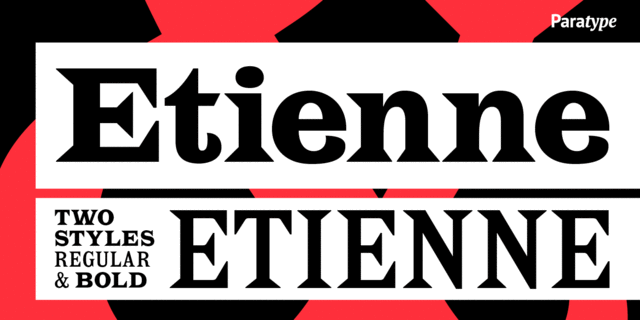
Шрифт разработан по мотивам рисунков гарнитуры Антик №8 и других подобных шрифтов XIX века (Латин Антик, Широкий Латин, Узкий Этьен, Широкий Ренессанс) для фирмы ParaType в 2002 году (дизайнер Тагир Сафаев). Шрифт так называемого латинского типа, с мощными треугольными засечками и довольно необычными завитками у некоторых строчных знаков. Тем не менее он великолепно подходит для широкого ассортимента работ в акцидении и рекламе.
Ассоциации c семейством EtienneКачества и характер:
острый, интересный, характерный, манерный, вычурный, причудливый, чудной, звонкий, оригинальный, старомодный, старинный, исторический, заметный, броский, азартный, резкий
Особенности семейства EtienneХит десятилетия:
Хит 1960-х Близкий исторический оригинал: